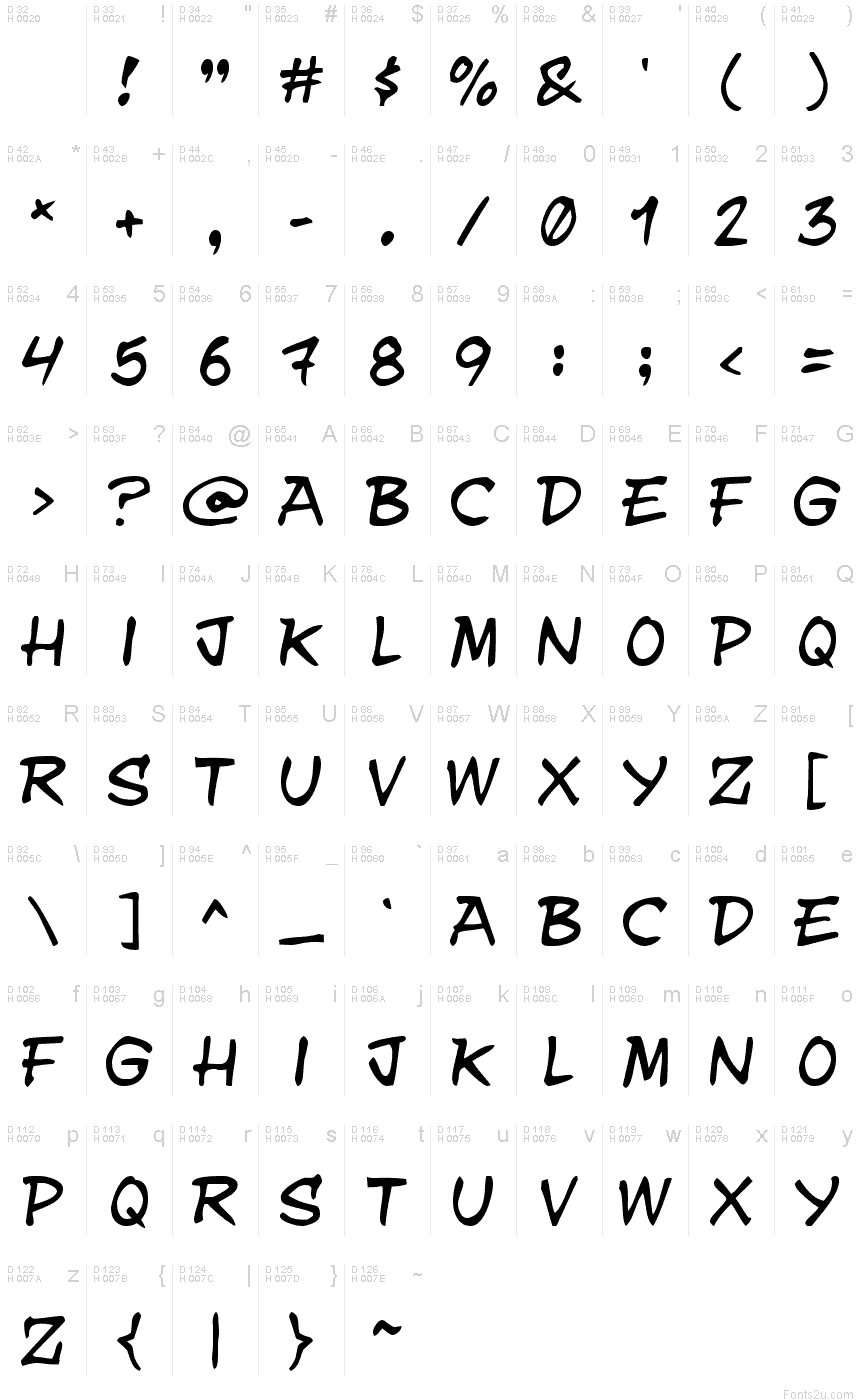
Y.N.W.U.A.Y, bezpłatny odręczny krój pisma w wielkich literach od Jakoba Fischera, stawia na luźny styl markera z wysokimi, nieregularnymi pociągnięciami oraz szybkimi, nieco niespokojnymi łączeniami. Litery balansują między wąskimi szczytami a szerokimi łukami, nadając pismu swobodny rytm, który sprawia wrażenie raczej nabazgranego niż dopracowanego.
Świetnie sprawdza się na plakatach, ulotkach muzycznych, grafikach skate czy streetwearowych, okładkach zinów i kartach tytułowych, gdzie surowy charakter pomaga nadać odpowiedni ton. Jako darmowy font, doskonale nadaje się również do krótkich nagłówków, monogramów i inicjałów, ponieważ ostre kąty i mocne krzywe niosą ze sobą mnóstwo charakteru nawet bez dużej ilości tekstu.